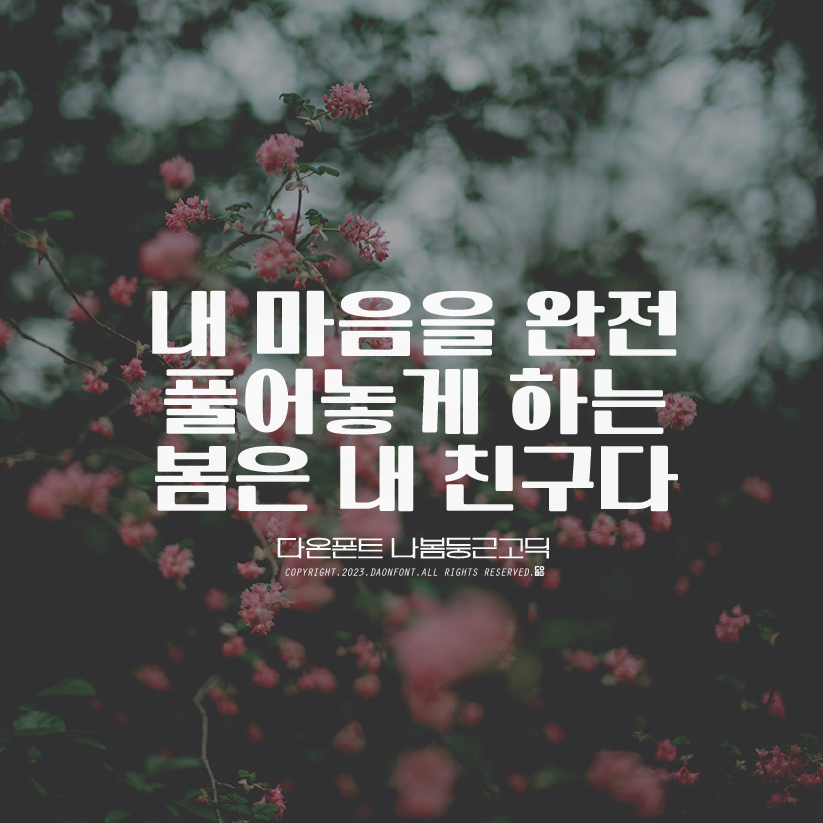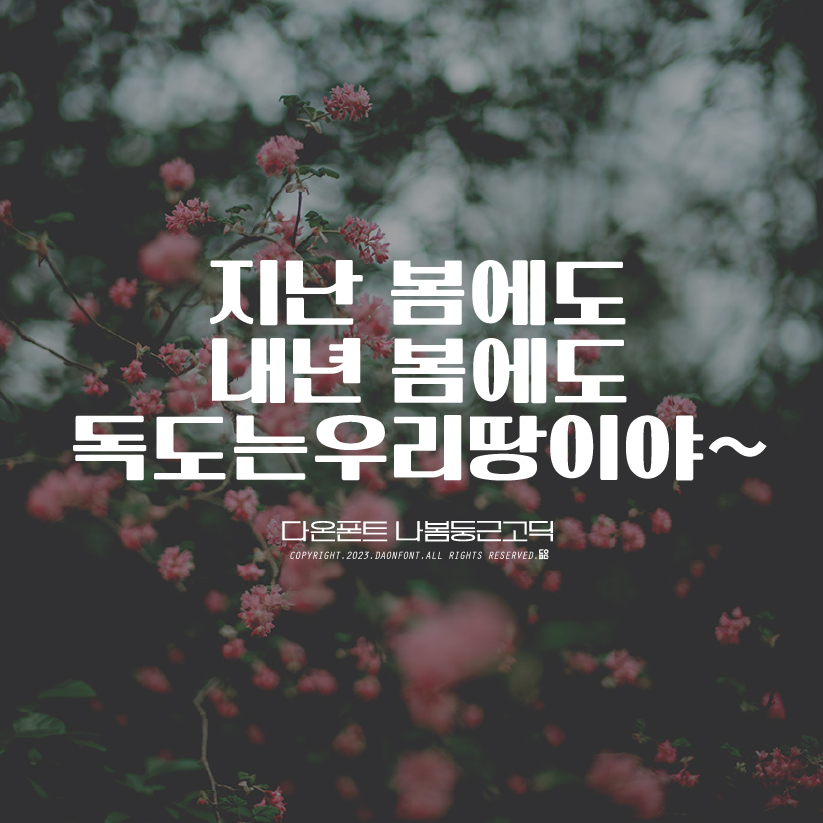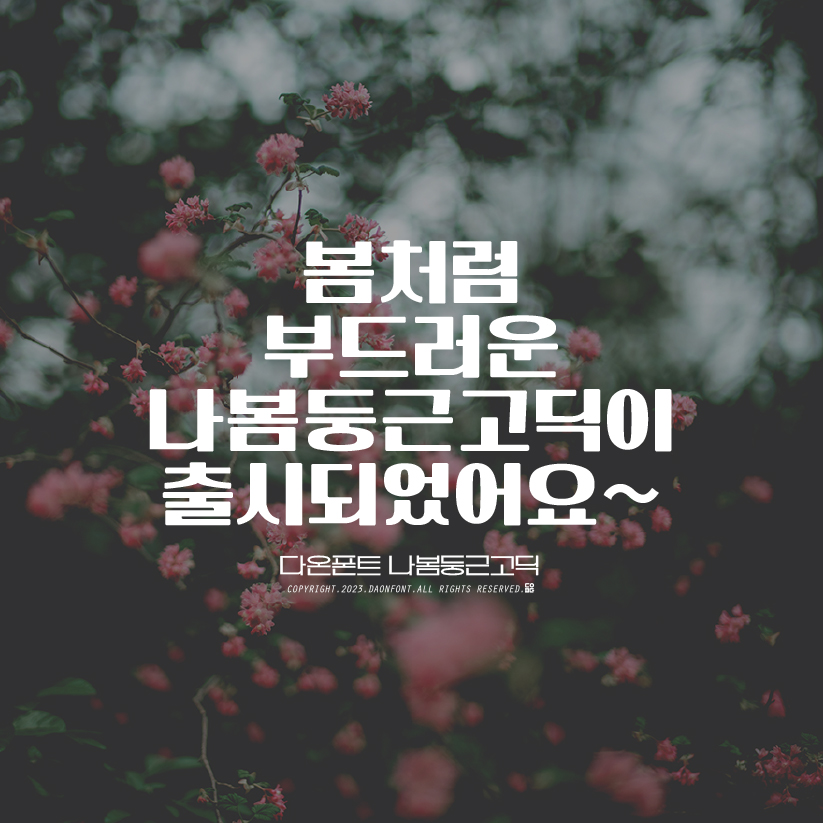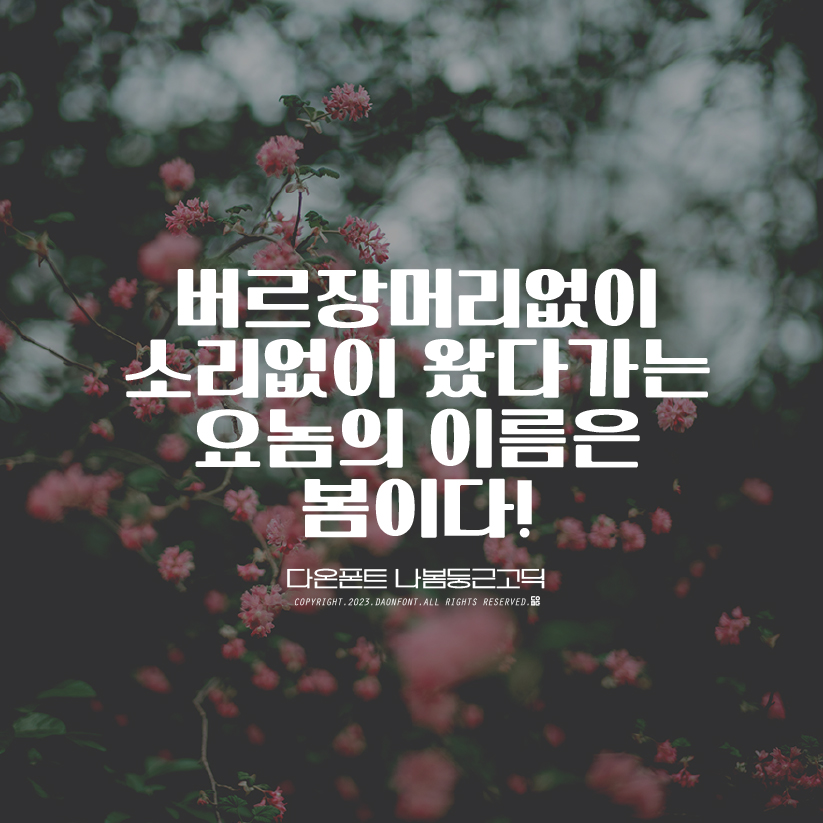
3월 네번째 신서체 다온폰트 '나봄둥근고딕' 출시
3월 네번째 신서체인 다온폰트 "나봄둥근고딕"이 업데이트 되었습니다.
다온폰트 "나봄둥근고딕"은 제목용으로 제작된 서체로
한글 2,780자, 영어 대/소문자, 숫자0~9, 특수문자, 딩벳으로 구성되었으며,
가로줄기와 세로줄기의 두께차이로 가독성이 좋아 여러용도로 사용하실 수 있습니다.